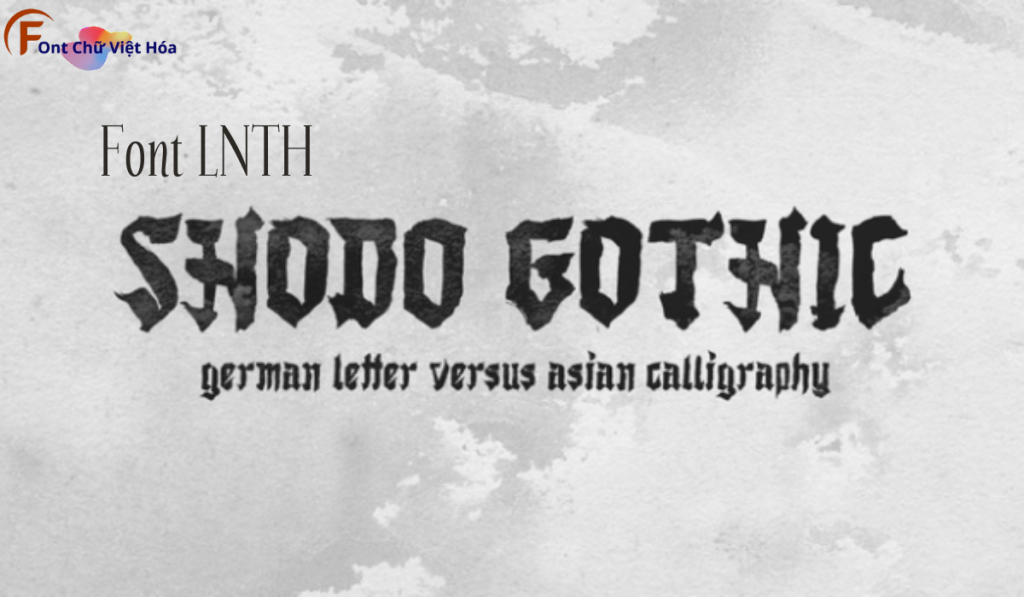
Font LNTH Shodo Gothic Việt Hóa
Tác giả: LNTH
Bộ Font: LNTH
Font LNTH Shodo Gothic Việt Hóa là một font chữ Gothic, thuộc bộ LNTH, với thiết kế mạnh mẽ và cá tính. Phong cách của font này phù hợp với các dự án cần sự nổi bật và ấn tượng, như poster, tiêu đề, hoặc bảng hiệu. Font LNTH Shodo Gothic Việt Hóa mang đến sự mạnh mẽ và dễ nhận diện, ứng dụng trong các lĩnh vực sáng tạo. Đặc điểm hình dạng của font bao gồm các đường nét dày và sắc sảo, giúp tăng tính thẩm mỹ và sự chú ý. Việc Việt hóa font giúp người dùng dễ dàng sử dụng trong các thiết kế tiếng Việt, mang lại sự tiện lợi và linh hoạt.